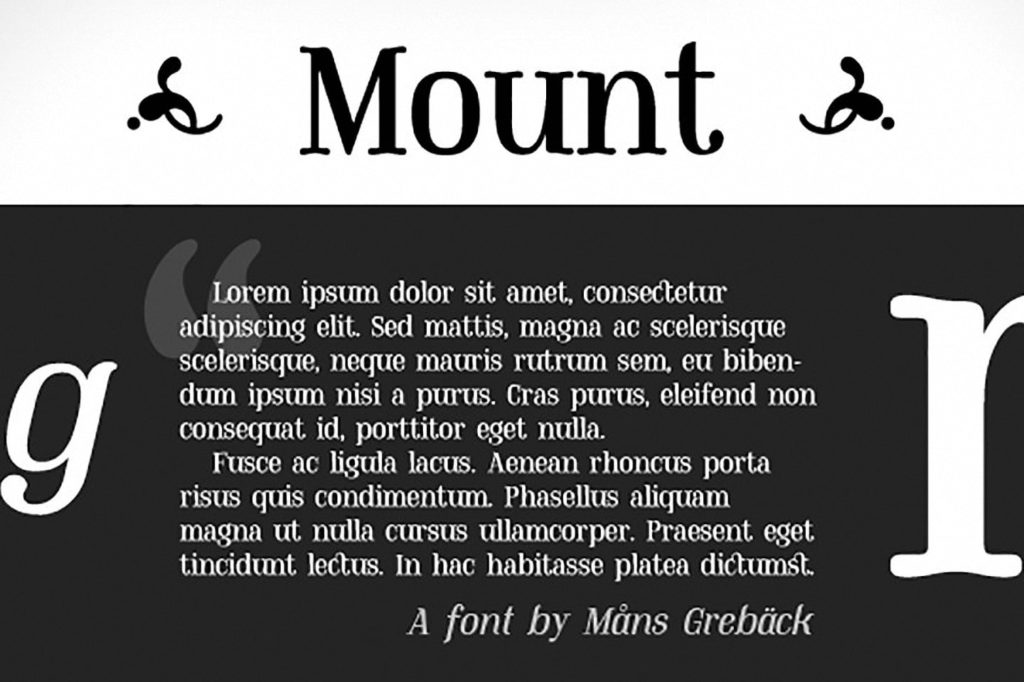
это утонченный шрифт с засечками (serif), созданный шведским дизайнером Мансом Гребэком (Måns Grebäck) в 2015 году. Он сочетает в себе строгую геометрию классической антиквы и мягкие, плавные изгибы, придающие буквам характерный винтажный шарм. Кириллическая версия была адаптирована для удобного набора текстов на русском языке, сохраняя оригинальную эстетику начертания. Этот шрифт идеально подходит для создания атмосферных заголовков, где важна выразительность и статусность. Вы можете **скачать бесплатно** базовые начертания для личных проектов, чтобы оценить его возможности в действии